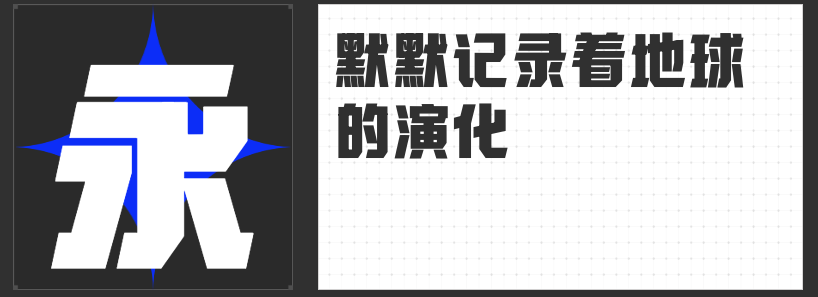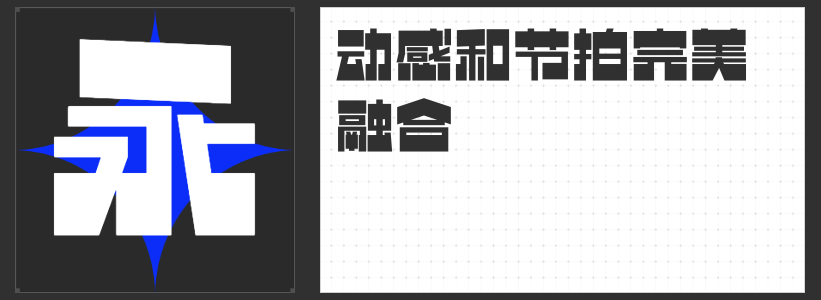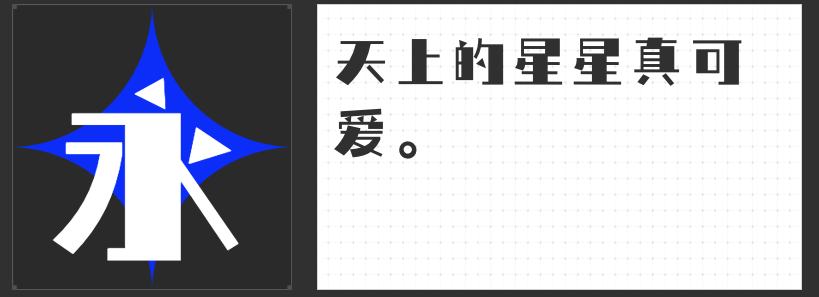
四款影视设计专属字体:以型载意,重塑视觉叙事美学
在影视设计的视觉语言中,字体不仅是信息载体,更是情绪与氛围的延伸。以下四款字体以独特的设计哲学与美学表达,为影视标题、字幕及场景文字注入灵魂,让每一帧画面都成为叙事的一部分。
一、也字工厂陨石黑
以“陨石”为灵感,这款字体以方正饱满的结构与偏上的重心,构建出如磐石般的稳定感。厚重的笔画与紧密的布白设计,赋予文字以雕塑般的坚实感,仿佛每个字符都承载着不可撼动的叙事重量。撇捺的统一化处理强化了块面感,使其在悬疑、历史或史诗题材中,能瞬间传递出庄严、深邃的视觉信号,成为画面中沉默却有力的叙事者。
二、励字造逆反差踢踏
通过颠覆传统字体的粗细逻辑,这款逆反差字体以“顶部厚重、中部纤细”的戏剧性对比,创造出如踢踏舞般的节奏感。直角的转折与对称的镜像设计,赋予文字以机械般的精准,而极细的中段笔画则如悬丝般牵引视觉焦点。在科幻、实验性或先锋题材中,其冲突感与现代性能打破常规,为画面注入锐利的未来主义气息。
三、喵字综艺体
专为综艺场景而生,这款字体以舞台灯光为灵感,将传统汉字的神韵与综艺的动态美学完美融合。笔画中隐藏的曲线与倾斜角度,模拟出镜头运动的光影轨迹,而局部的夸张变形则如即兴表演般充满惊喜。在娱乐、真人秀或轻喜剧题材中,其活泼却不失秩序的设计,能瞬间激活画面氛围,成为连接观众情绪的视觉桥梁。
四、励字造桃气圆 大粗
以手写感为基底,这款圆体通过“上松下紧”的错落结构与圆润饱满的笔画,传递出如棉花糖般的柔软质感。折笔处的内外圆角与笔画间的“留白呼吸”,让文字在密集信息中依然保持轻盈。在家庭、爱情或治愈系题材中,其温暖而不失现代感的设计,能为画面增添一抹人性化的温度,让文字成为情感的触点。
这四款字体以风格化的设计语言,重新定义了影视文字的叙事潜能。无论是力量的凝聚、张力的释放、趣味的激活还是温度的传递,它们都能以型载意,让文字成为影视视觉中不可或缺的“第四维度”。